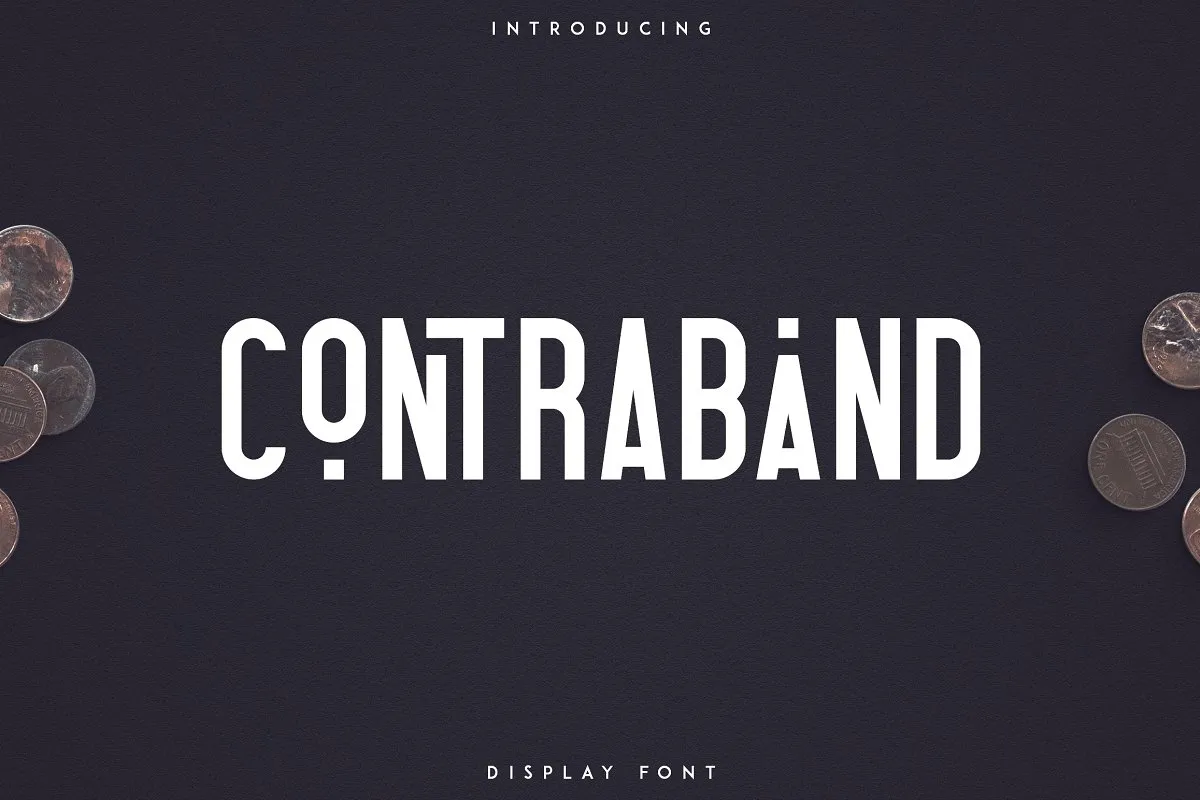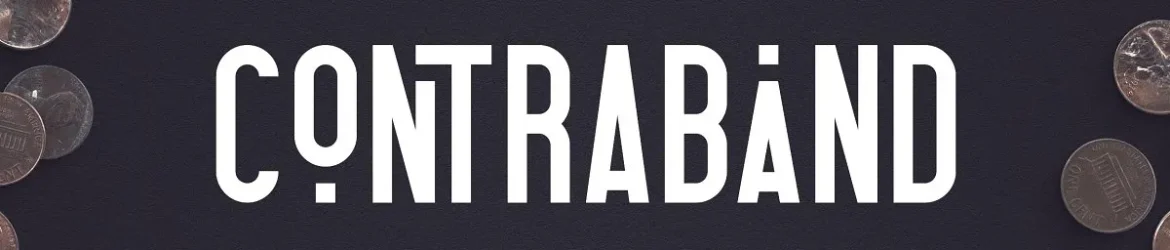
A Contraband Display Font é uma fonte de exibição vintage criada pela VPcreativeshop, perfeita para qualquer projeto de design que precisa de uma personalidade forte e um toque vintage. Com seu desenho limpo e sem graça, esta fonte oferece inúmeras alternativas de caracteres, ligaturas e suporte multilíngue, tornando-a versátil e capaz de adaptar-se perfeitamente em tamanhos grandes ou pequenos. Especialmente adequada para projetos de marca, designs para objetos domésticos, embalagens de produtos e cabeçalhos de revistas, a Contraband também é perfeita para uma overlay estilizada de texto sobre qualquer imagem de fundo. Seja em uma campanha de marketing digital, um design de produto ou até mesmo um mural de loja, esta fonte certamente dará o toque definitivo ao seu trabalho. Com sua elegância única e estilo vintage moderno, a Contraband Display Font é definitivamente algo que você não quer deixar de lado em qualquer projeto visual.